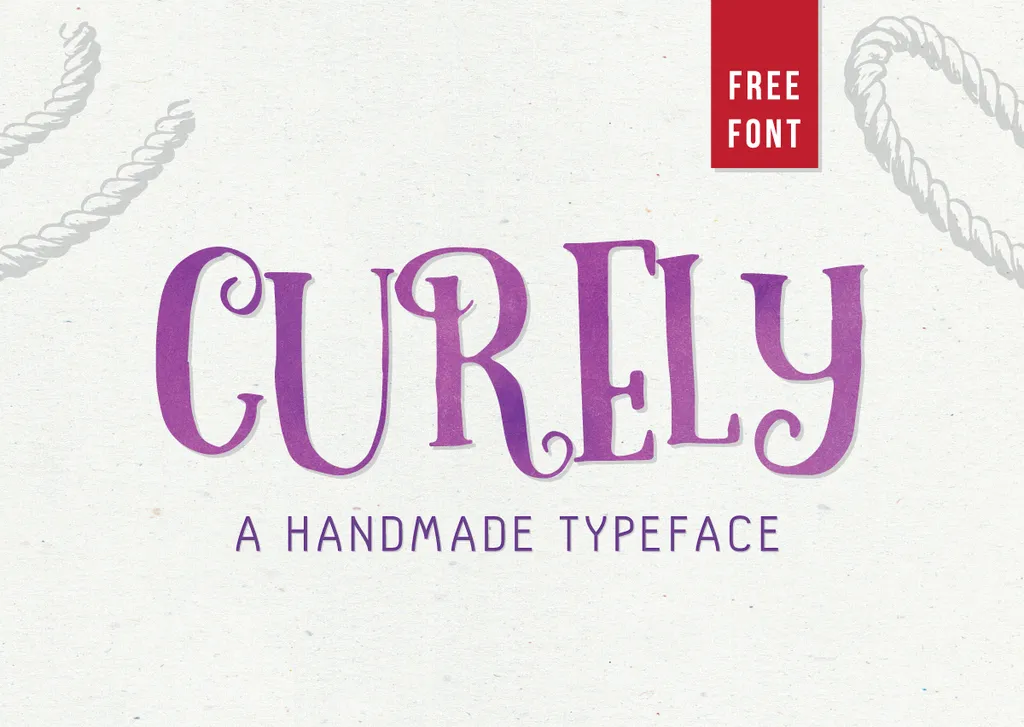
A Curely é uma fonte de tipografia com personalidade, inspirada nas pequenas coisas encantadoras que permeiam cada letra. Ela foi criada para dar vida à sua criação lúdica e sensível, seja um design gráfico ou em outras formas de expressão artística. Seus traços delicados se assemelham a uma caligrafia manual, mas são perfeitamente personalizados para atender aos seus projetos criativos que exibem charme e ternura. Não apenas é adequada para criações lindas e delicadas, mas também tem um toque de irreverência que encanta. Ideal tanto para designers quanto para amantes da arte, a Curely traz vida à cada projeto com sua composição única e encantadora.